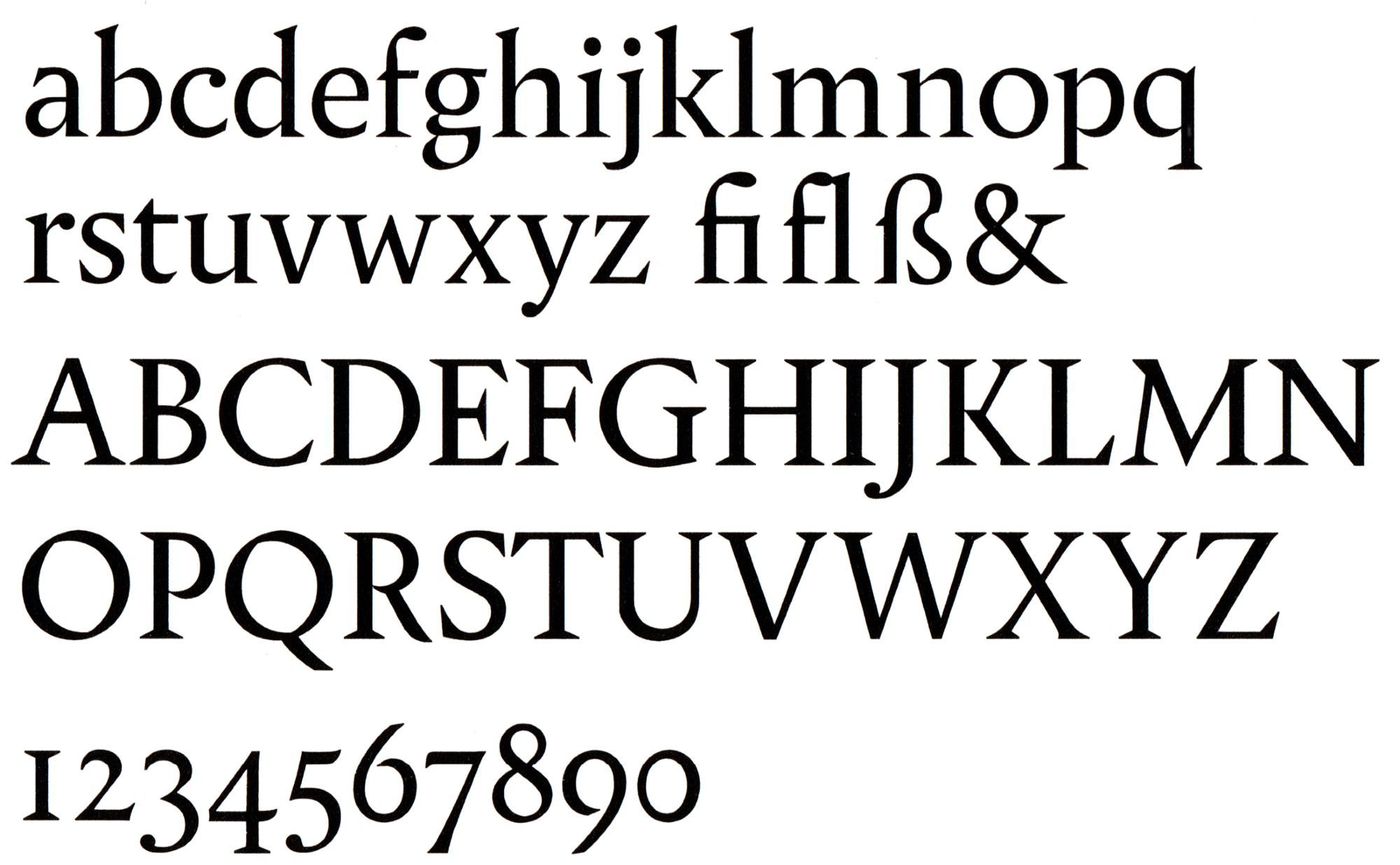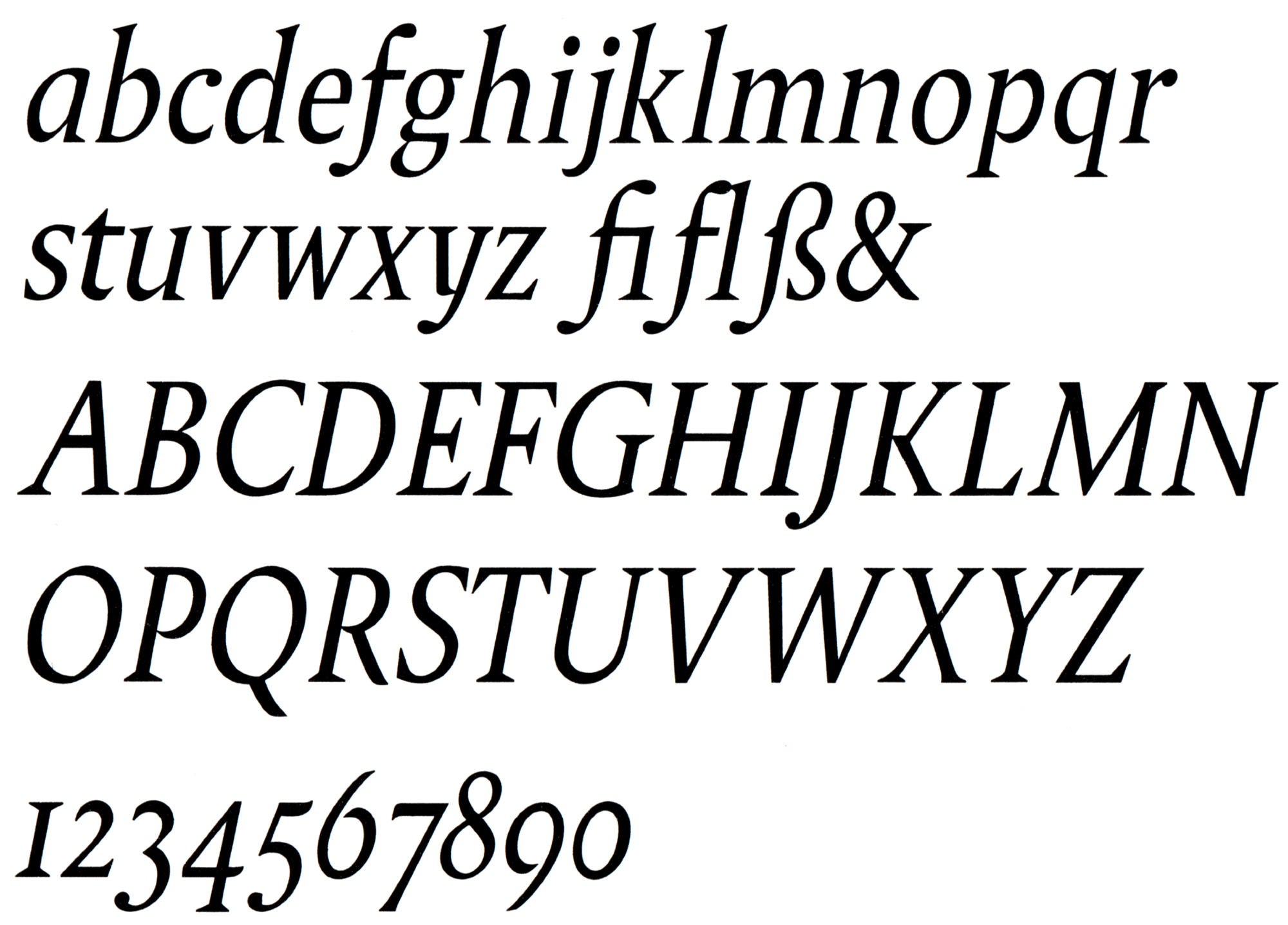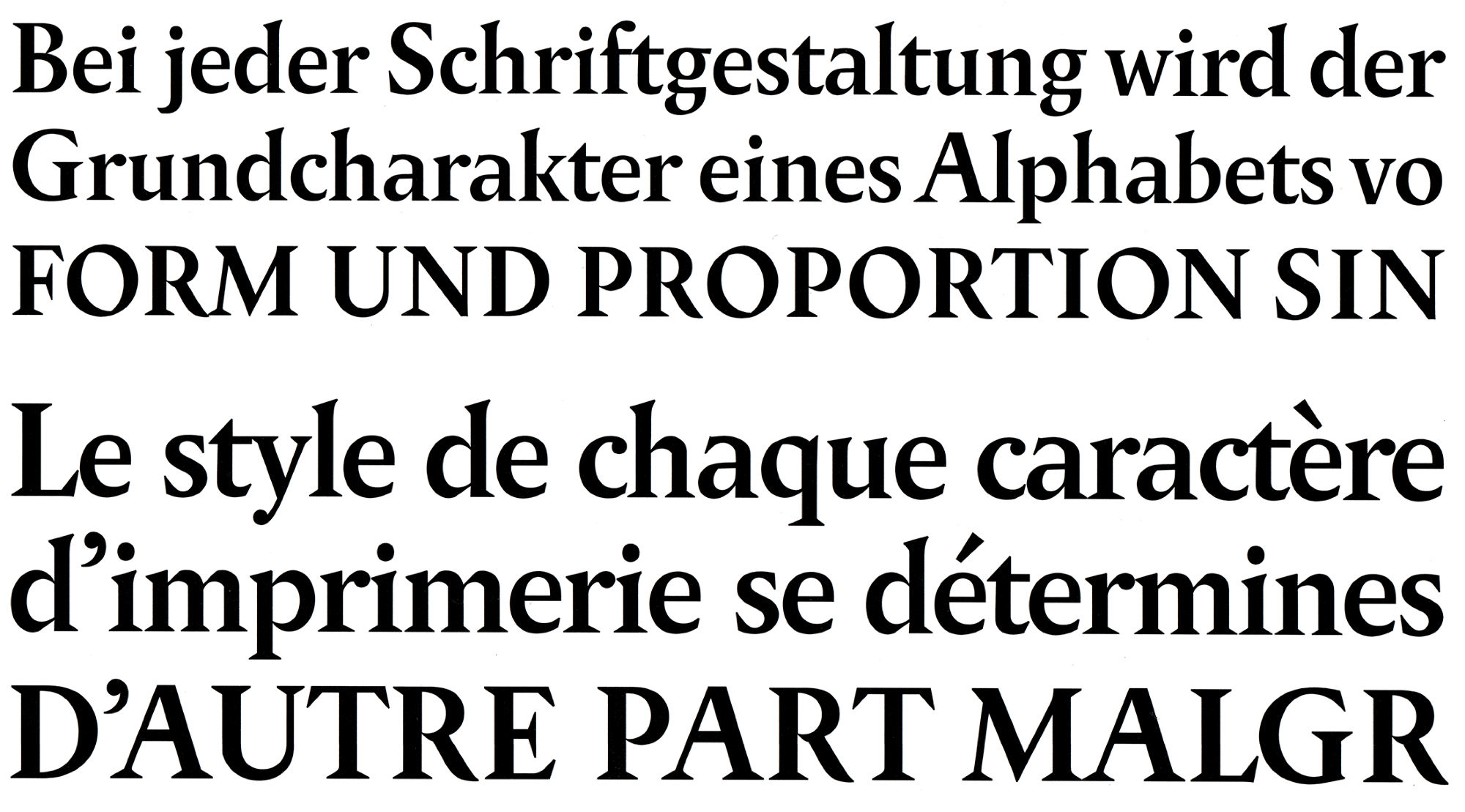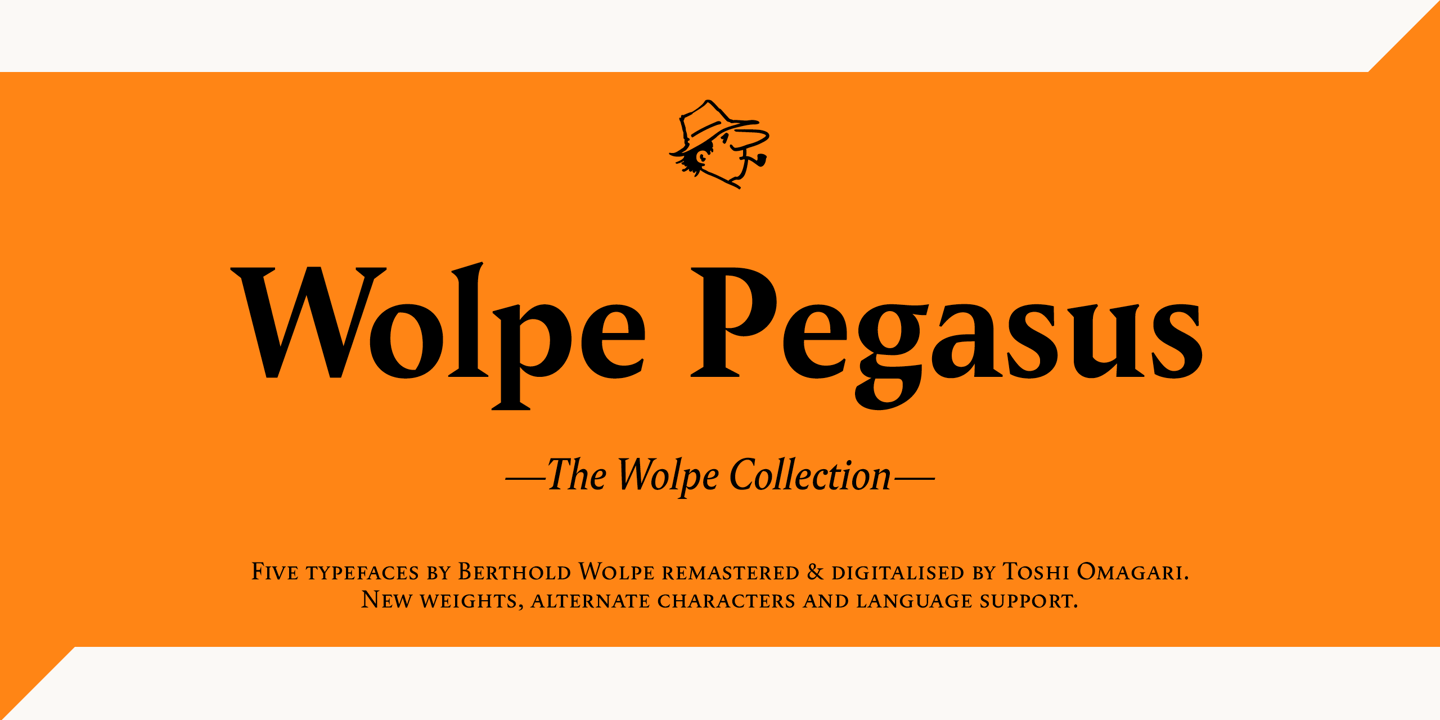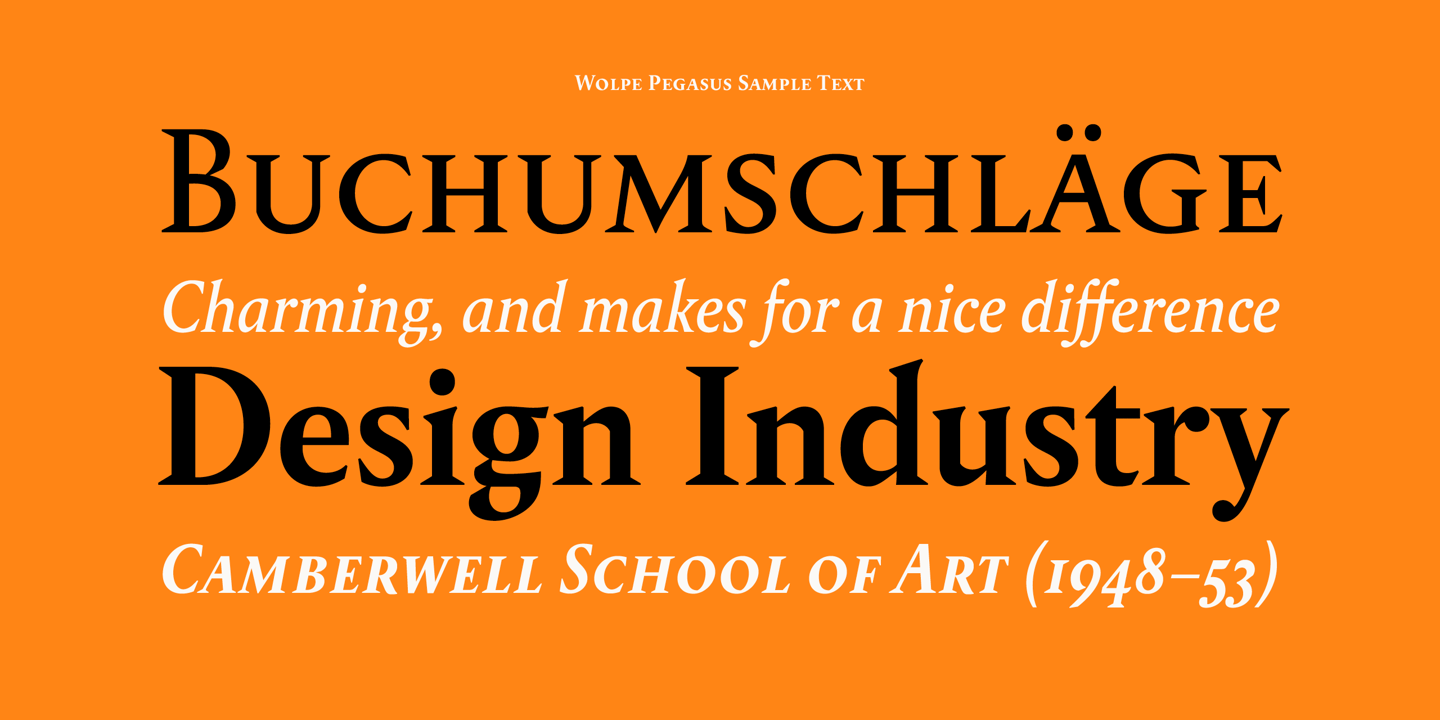
Font-Wiki: Pegasus
Die Pegasus ist eine Textschrift von Berthold Wolpe und wurde 1937 über Monotype als Bleisatzschrift veröffentlicht. Eine Erweiterung erfolgte in den 1980er-Jahren durch Matthew Carter für Linotype. Heute ist die Schrift als Wolpe Pegasus in einer weiteren Überarbeitung durch Toshi Omagari erhältlich.